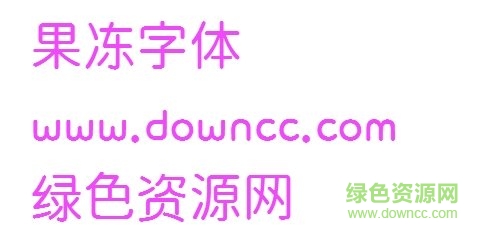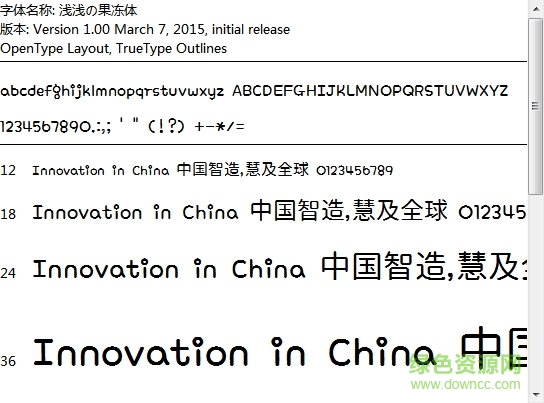
淺淺果凍字體是一款造型上十分Q萌可愛(ài)的藝術(shù)字體,給人如果凍般潤(rùn)滑流動(dòng)的動(dòng)態(tài)體驗(yàn),結(jié)構(gòu)疏松而整體清爽,給人極佳的視覺(jué)效果,可用在兒童相關(guān)和趣味內(nèi)容的修飾上,綠色資源網(wǎng)獨(dú)家推薦!
果凍字體是由淺淺美化修飾的一款特色卡通字體,但字里行間并無(wú)各種復(fù)雜的裝飾,讓文字更顯質(zhì)樸清新!